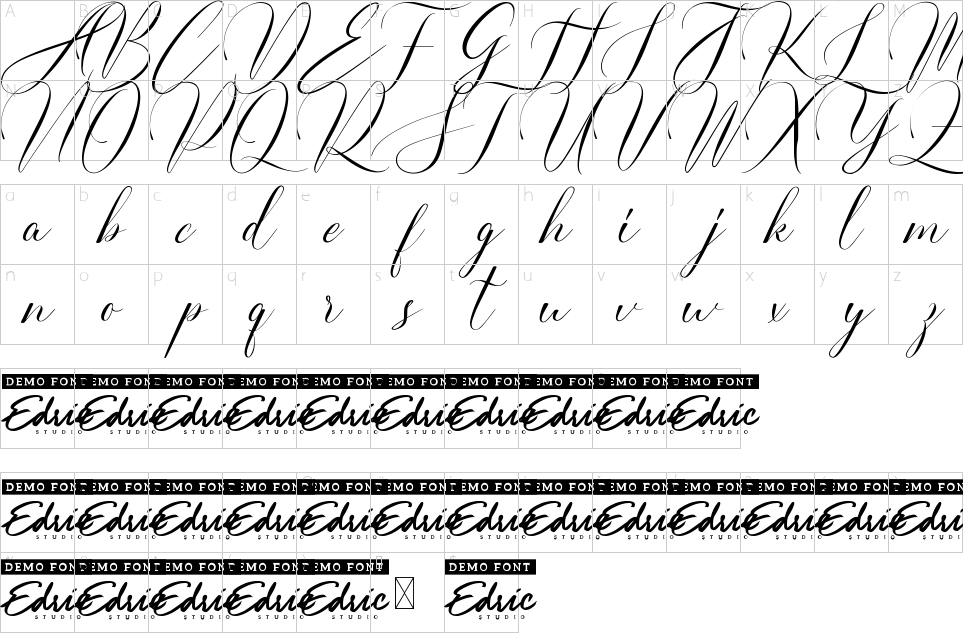
Descubra a beleza única do Grand Estonia Font, uma elegante seleção de caracteres que adicionarão sofisticação à sua próxima obra de arte digital. Desenvolvida pelo incrível Designer EdricStudio, este font é um verdadeiro prato cheio para designers e criativos buscando algo mais além das fórmulas padronizadas. O Grand Estonia vem em versões compatíveis com Windows e Mac, garantindo a maior liberdade de expressão na criação digital. Com 2,946 downloads ao longo do tempo, é evidente que os criativos adoram seu estilo distintivo e versátil. Tente ele hoje e veja como essa font pode transformar seus projetos digitais para sempre.